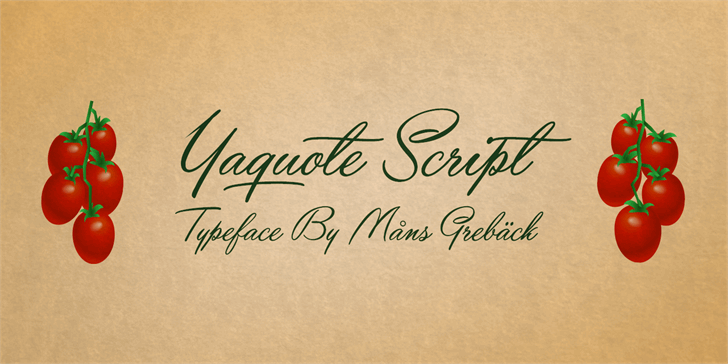
A fonte Yaquote Script é uma escolha perfeita para anúncios comerciais memoráveis ou projetos de marketing digital com um toque sofisticado e elegante. Seus traços fluidos e nuances sutis dão vida a qualquer texto que esteja em sua superfície, criando imagens vibrantes e envolventes. Criada pelo designer Hamilton, esta fonte é uma criação única para aqueles que buscam algo diferente no mundo das fuentes de scripts. Seu uso não apenas tornará seu projeto mais atraente, mas também o deixará com um toque pessoal e imediatamente reconhecível. Para quem quer ter acesso exclusivo à este incrivelmente detalhado design, visite o site da Mansgreback para adquirir uma licença comercial. Com Yaquote Script, você pode transformar simples mensagens em elementos de destaque que chamam a atenção e criam uma memória duradoura em seus leitores.